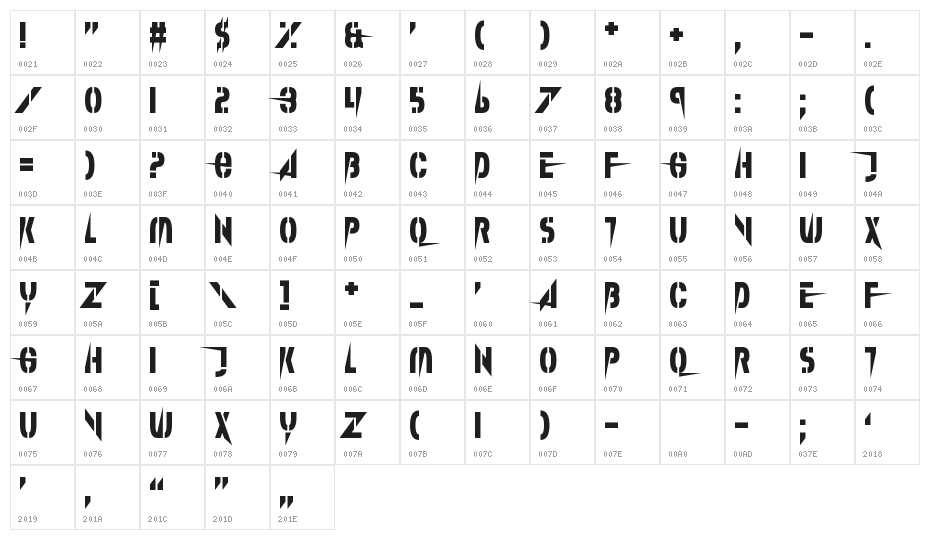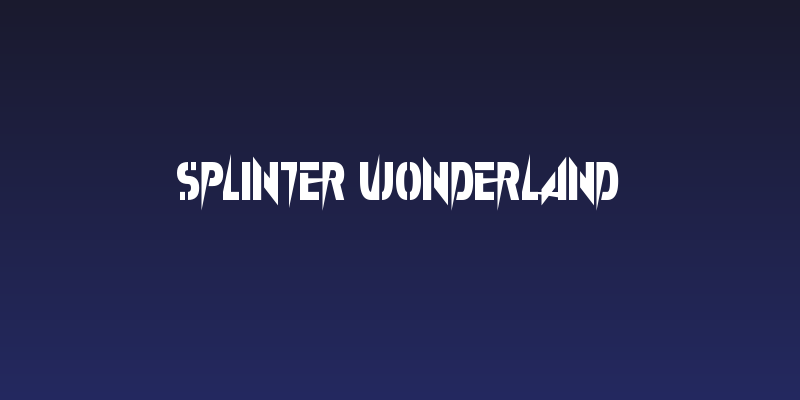
Splinter Wonderland Font
| Stile generale | Modern, Avant-garde |
| Caso d'uso | Headlines, Logos, Artistic projects |
| Progetti proposti | Ideal for album covers, posters, branding for edgy or modern products, and artistic projects requiring a bold statement. |